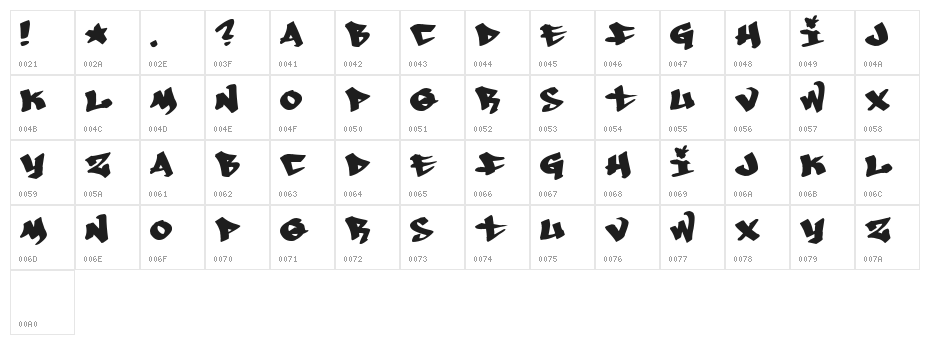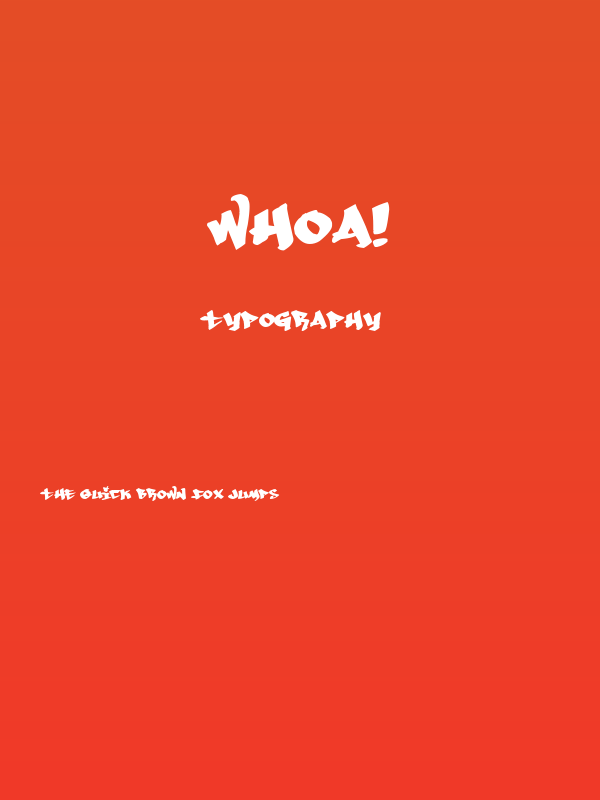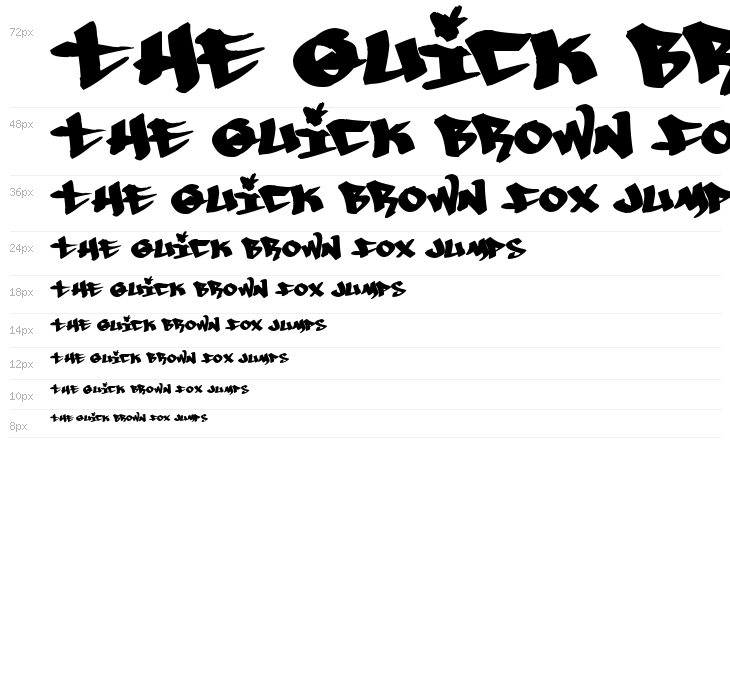
Whoa! Font
✎ Graffiti
| 整体风格 | Urban, Graffiti, Energetic |
| 推荐项目 | Ideal for street art-themed projects, urban branding, edgy posters, and music album covers. |